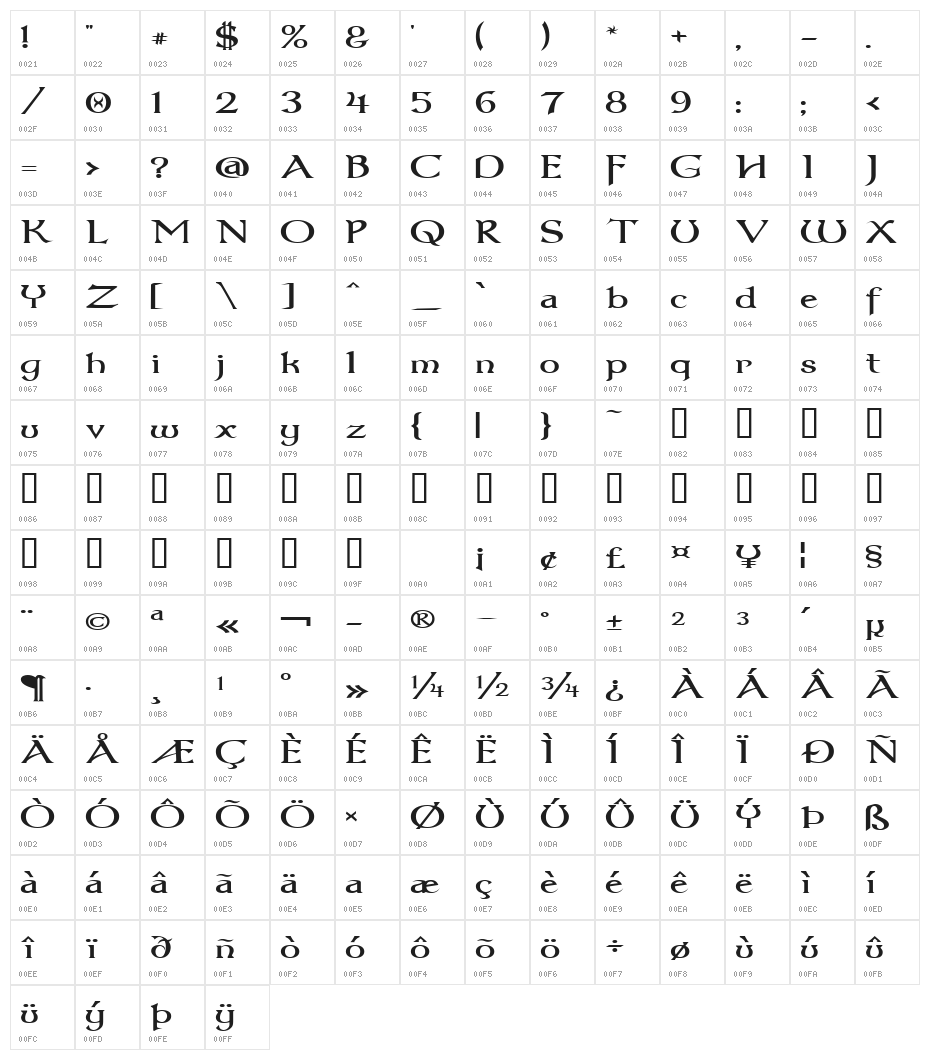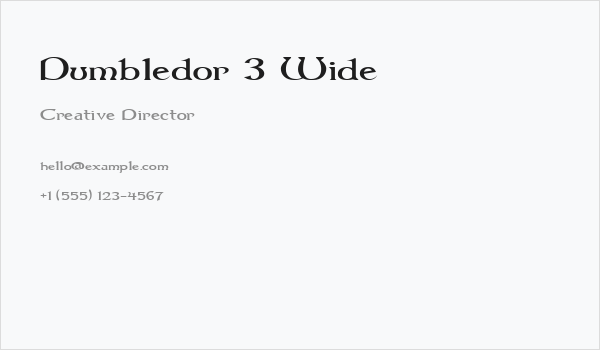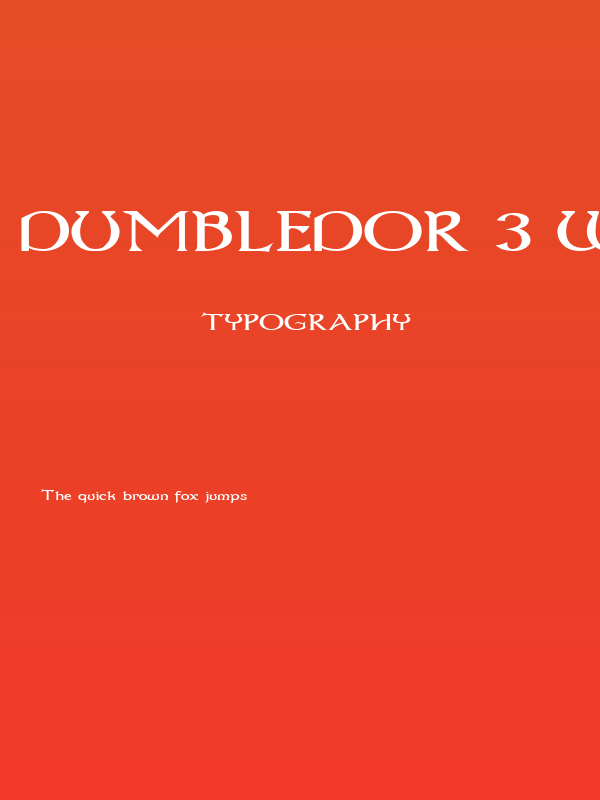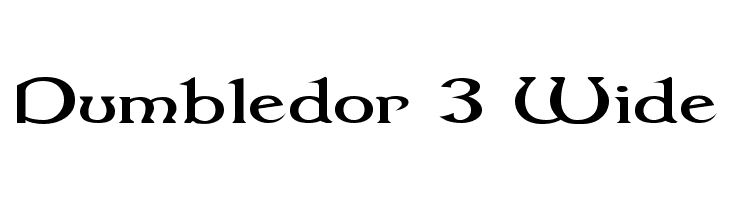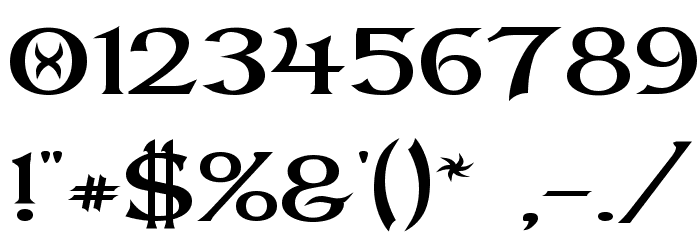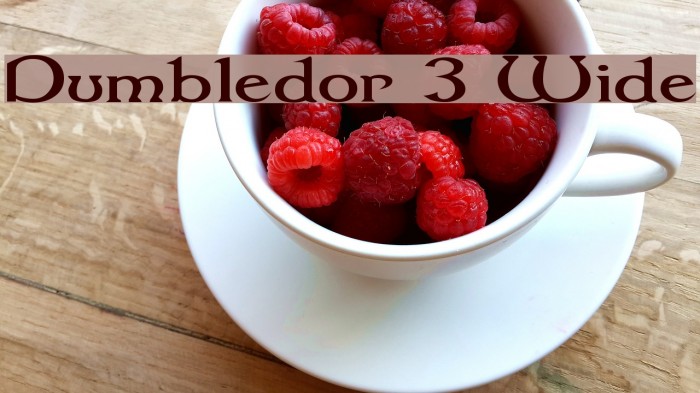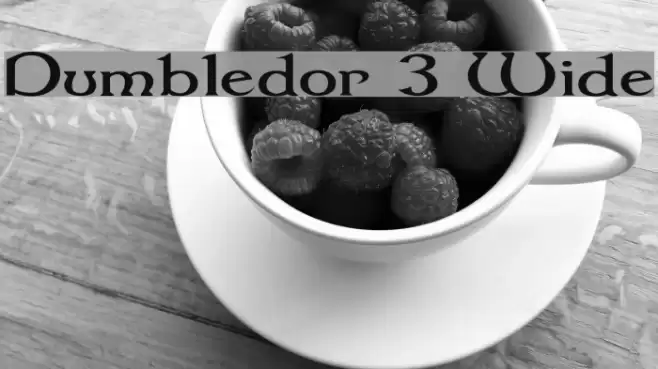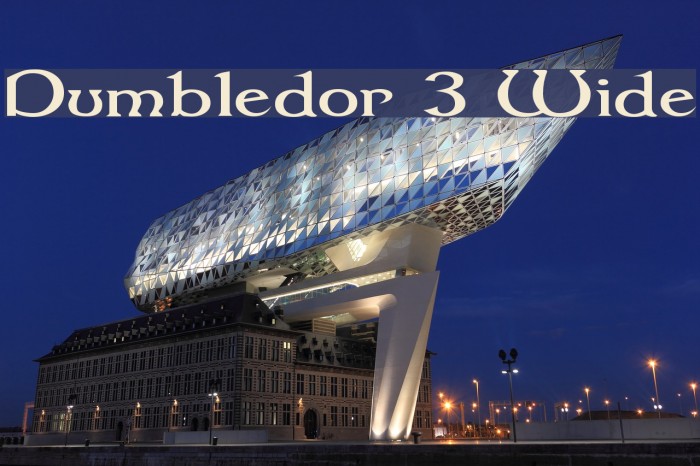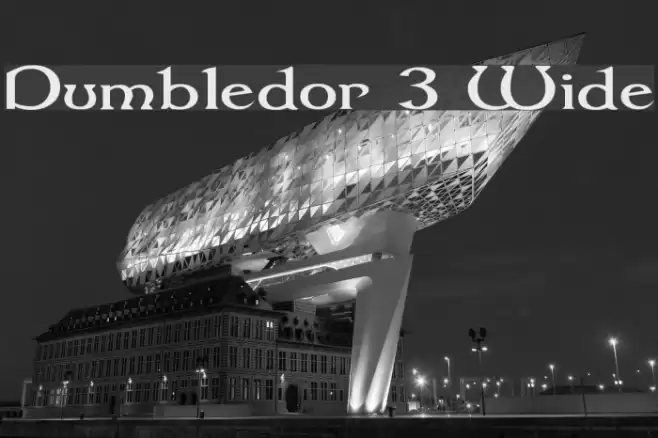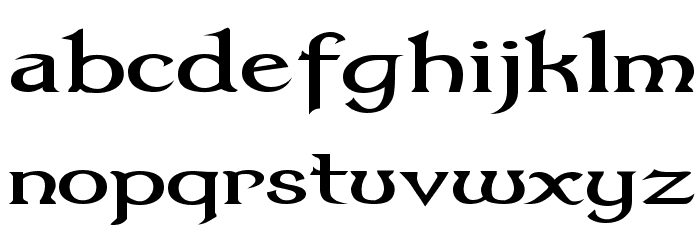
Dumbledor 3 Wide Font
Fonts by Graham Meade - GemFonts
| Estilo general | Vintage |
| Proyectos propuestos | Ideal for fantasy book covers, historical event posters, themed invitations, and video game titles. |